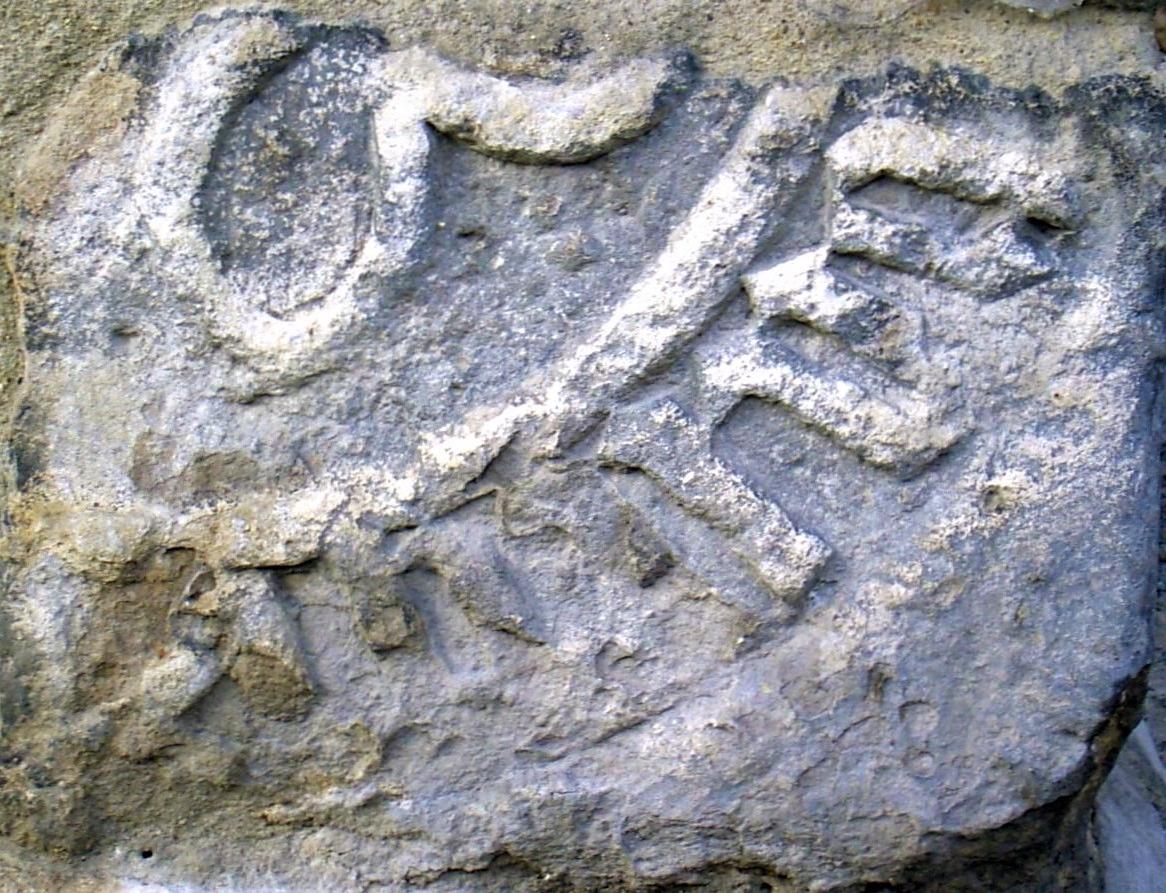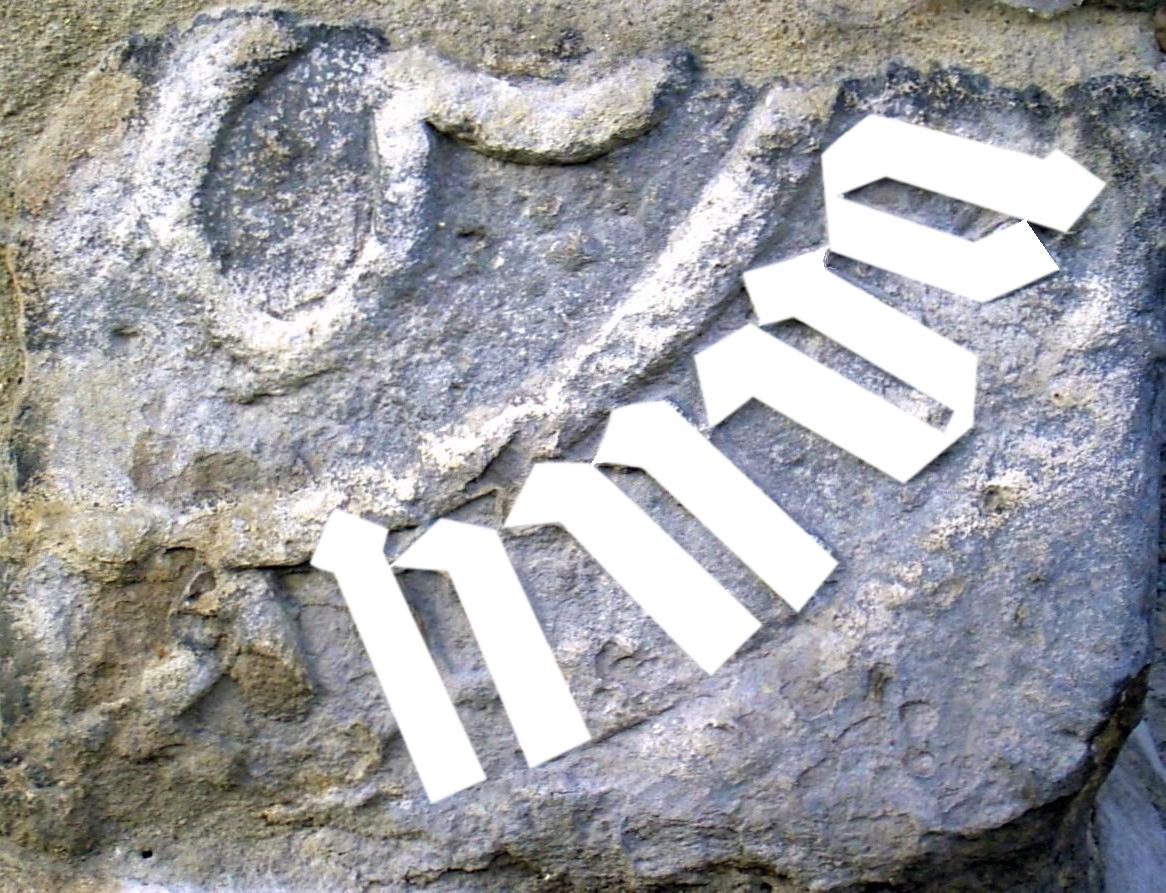
Seit langem beschäftigt mich ein Eckstein in einem alten Gebäude in Weißensee / Thür. Er enthält einen Teil einer Inschrift die nach gotischen Minuskeln aussieht. Der Stein ist bestimmt von einem älteren Gebäude (Stadttor?) und wurde dann wieder neu verbaut. Er hat die Maße  63x46x30 (BxHxT)
obwohl ich noch keinen Sinn sehe, ist deine Deutung der Buchstaben am wahrscheinlichsten. Könnte das "Symbol" in der Mitte ein Kleeblatt sein?